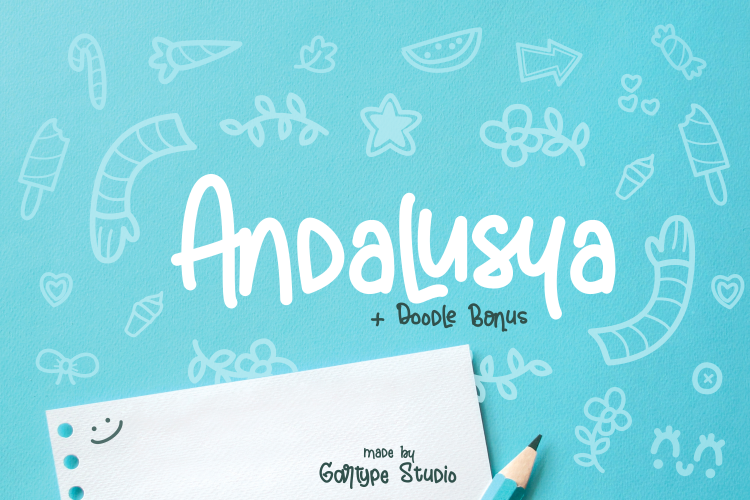
Andalusya Script Font – Fonte Grátis
Andalusya Script Font
Andalusya Script Font é uma fonte casual e divertida criada para oferecer um toque especial aos seus projetos digitais. Seja ela a escolha perfeita para adicionar um ar descontraído ao seu design, seja como quote, logomarca, marca personalizada ou qualquer outro elemento visual que deseje destacar. Este script font não apenas eleva o nível de profissionalismo em seus materiais de marketing e identidade corporativa, mas também adiciona uma dose extra de diversão e personalidade. Gartype Studio oferece um benefício adicional: a oportunidade de incorporar desenhos amorosos para tornar ainda mais atraente sua necessidade. Este recurso é perfeito para aqueles que buscam um pouco de encanto em seus projetos, seja para uma campanha publicitária ou para finalizar um documento importante. A Andalusya Script Font é uma escolha inteligente para quem procura um equilíbrio entre criatividade e simplicidade, transformando qualquer projeto no qual for usada.
Designer: Gartype Studio